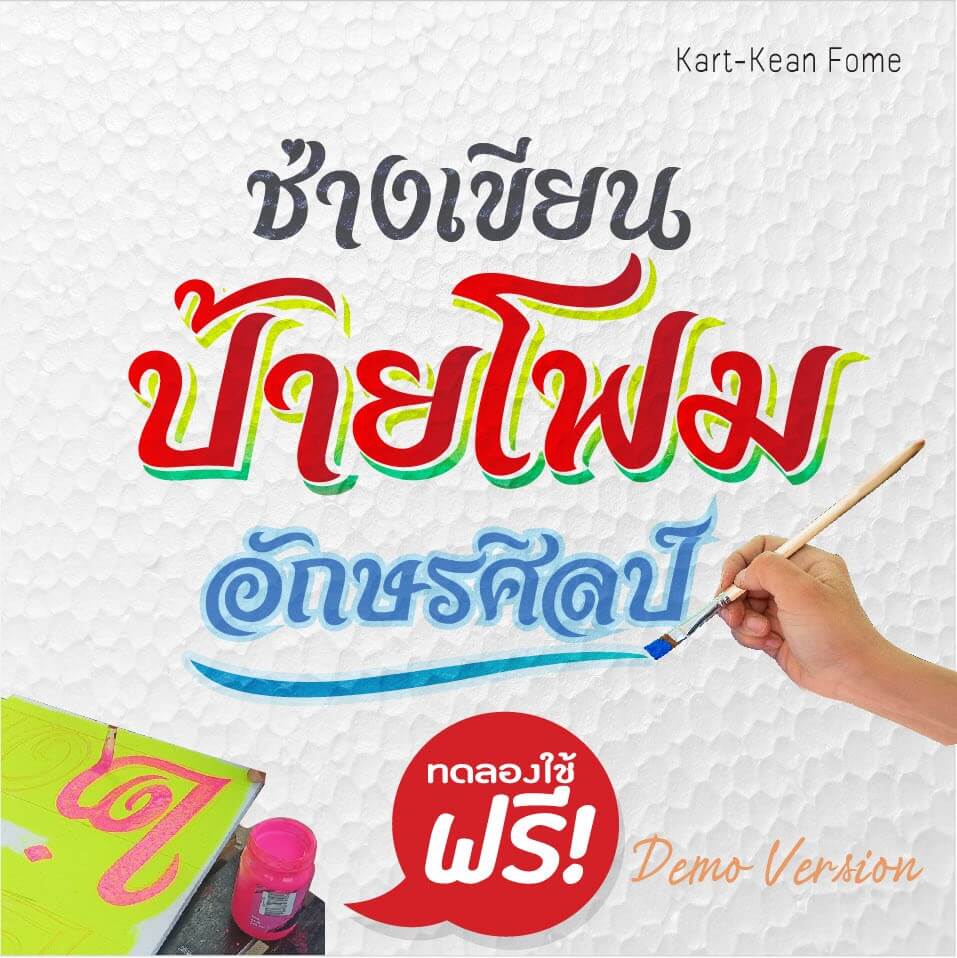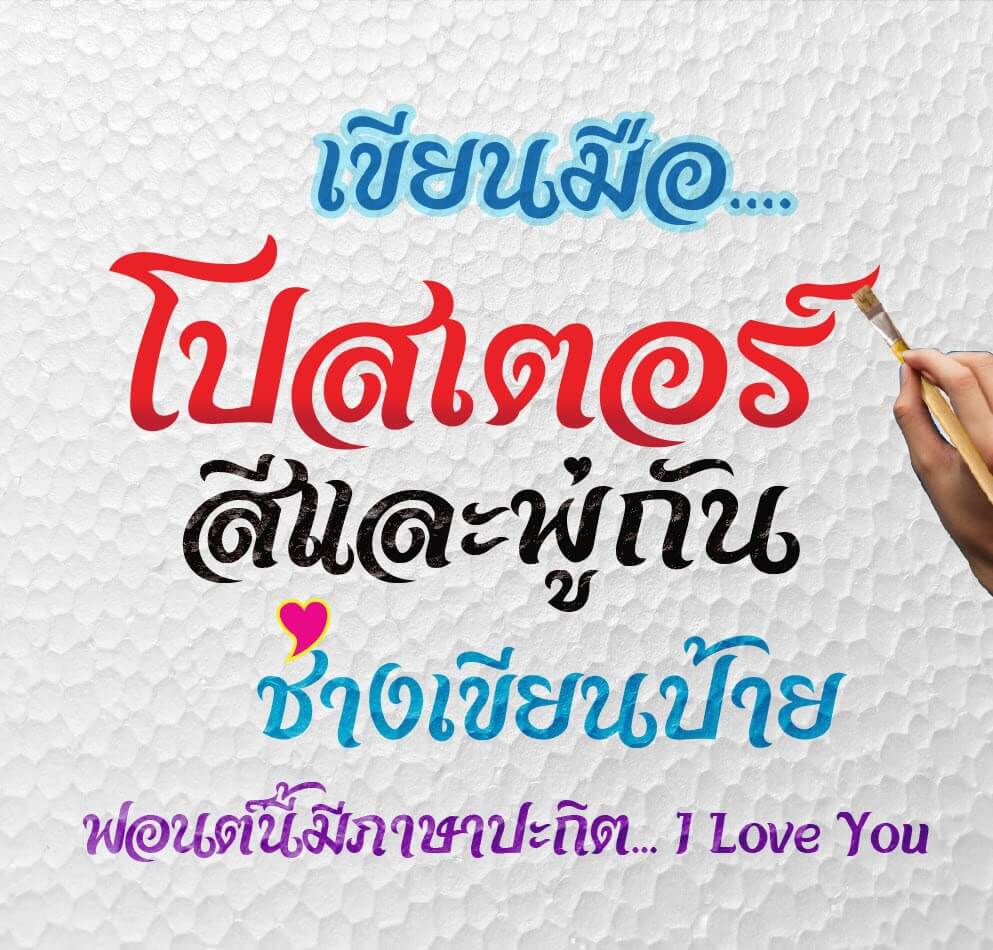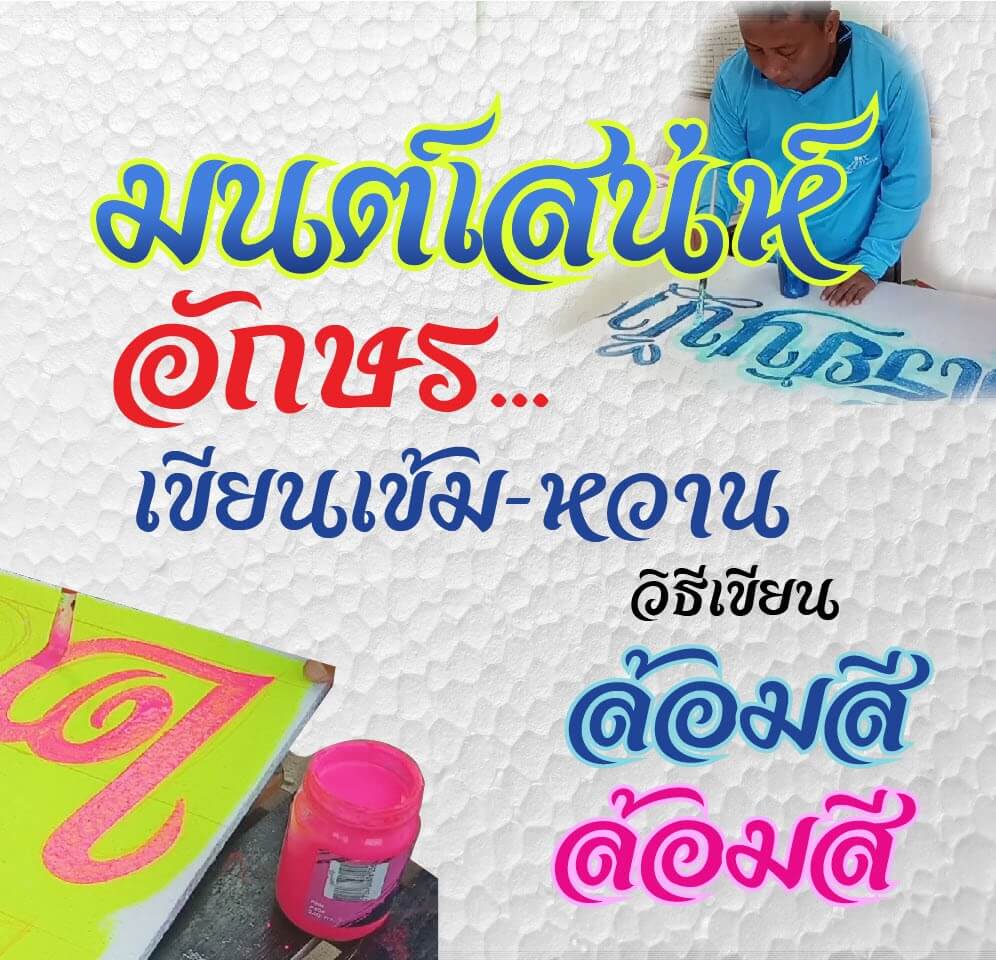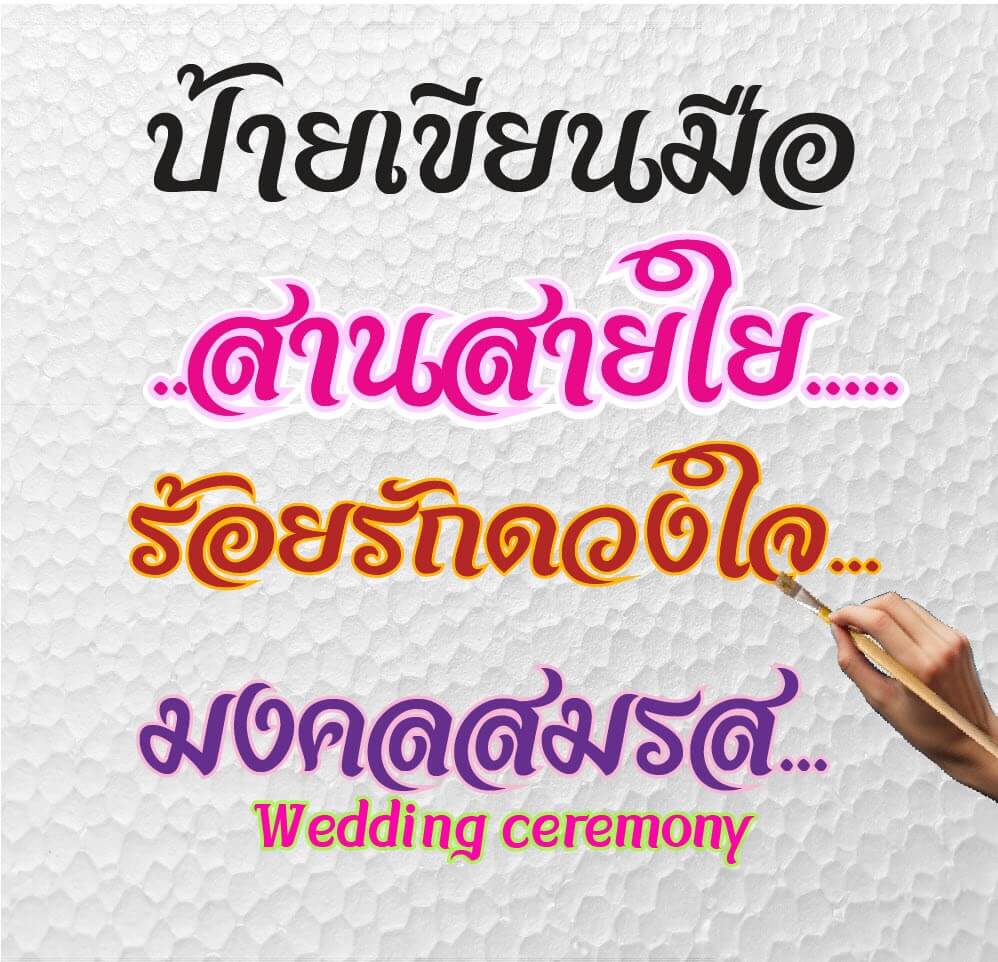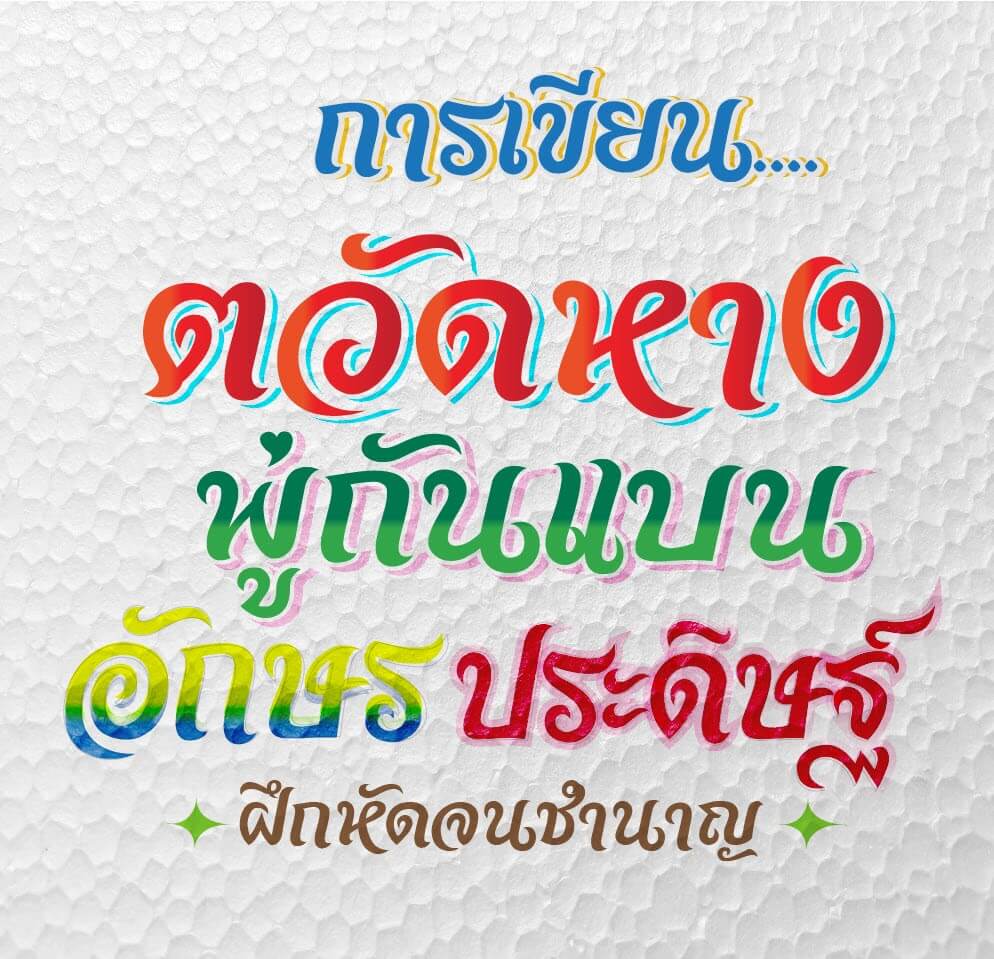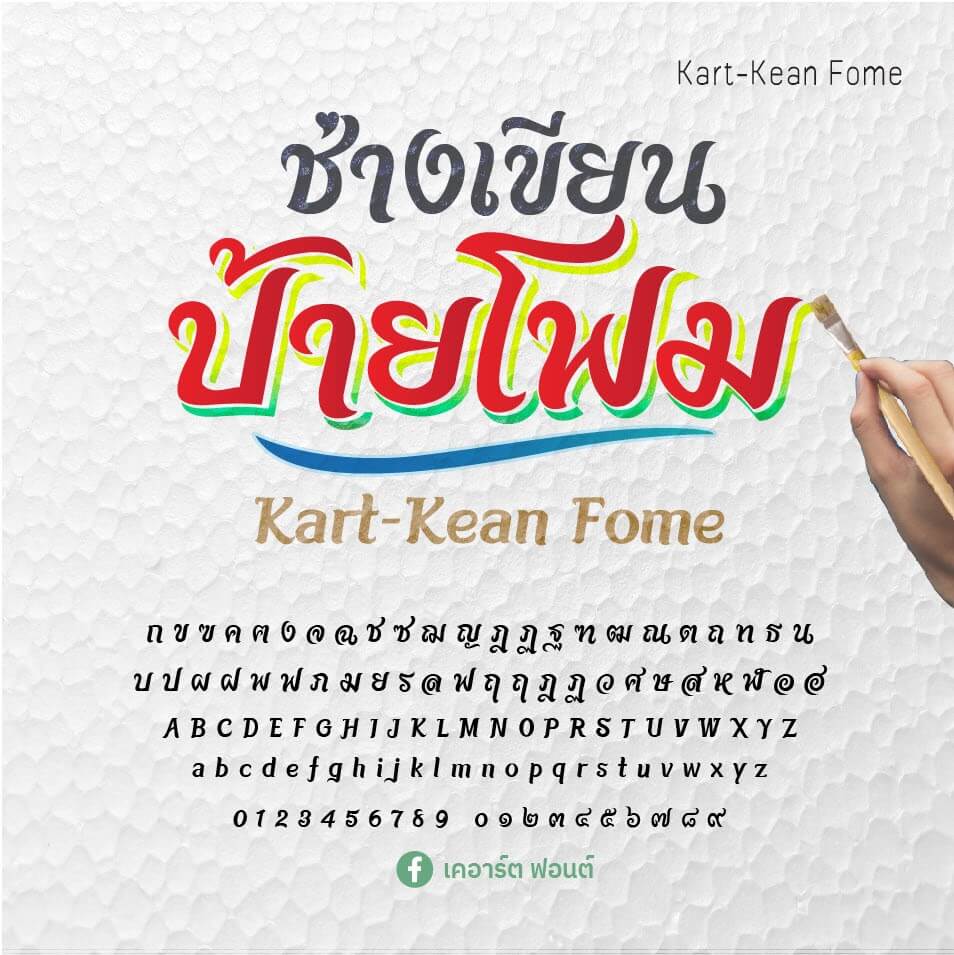
เคอาร์ต ลายไทย – เป็นฟอนต์ที่เขียนขึ้นจากแรงบันดาลใจจากลายมือศิลปินอักษร ผู้ใช้แปรงพู่กันสร้างสรรค์ผลงานมาอย่างต่อเนื่อง ด้วยความชอบและจำติดตาในหลายผลงานป้ายโฟม ป้ายโปสเตอร์ในอดีตวันวาน ซึ่งงานเขียนมือแบบนี้มากคุณค่ามากๆ
เคอาร์ตเขียนโฟม (Kart-Kean Fome)